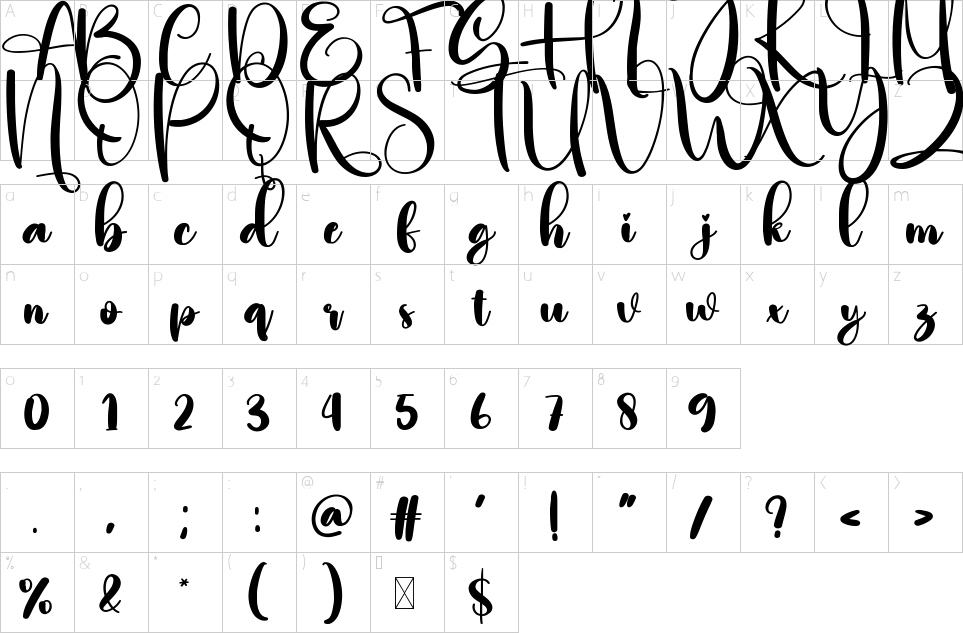
Aqui está uma descrição para a página de download da font ‘Darling’ em português do Brasil: Descubra a delicadeza e a elegância da fonte Darling, desenhada com um estilo único que combina suavidade e sutileza. Perfeita para decorar sua marca ou aplicar em designs pessoais, esta fonte oferece uma experiência de uso confortável e criativa. Disponível tanto no Windows quanto no Mac, a Darling é ideal para aqueles designers que valorizam uma escolha personalizada e original em seus trabalhos. Desenvolvida por scratchones, esta font foi adquirida pela comunidade digital mais de 740 vezes, demonstrando seu impacto e qualidade. Experimente a Darling: sua marca ganhará um toque aveludado e único com essa fonte gratuita que oferece uma variedade de estilos para personalizar. Perfect para criar gráficos profissionais ou simplesmente dar vida a seus projetos pessoais, a Darling é uma escolha inteligente para qualquer designer em busca de algo inovador e sofisticado.